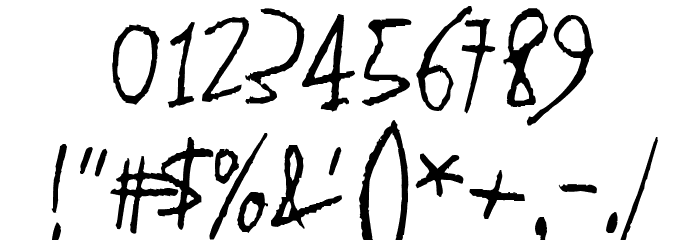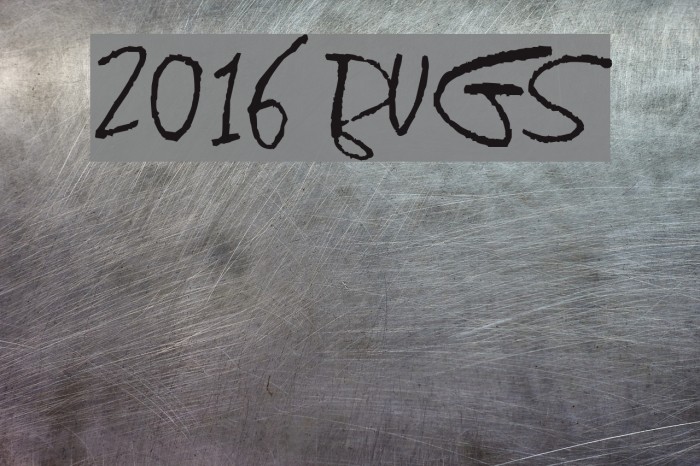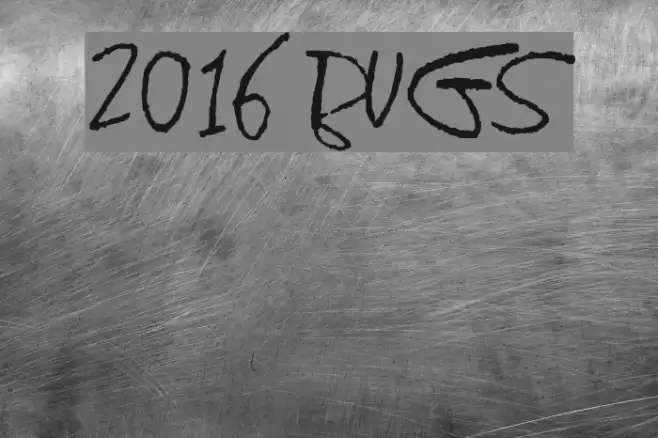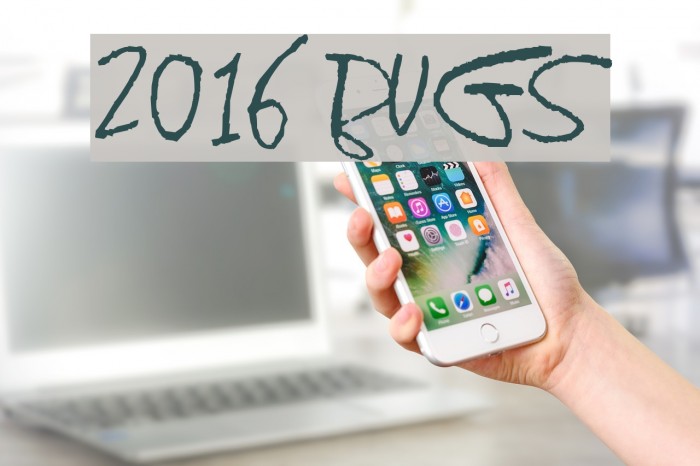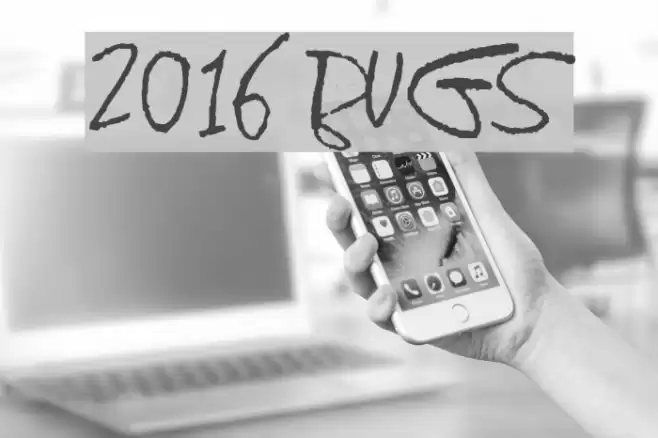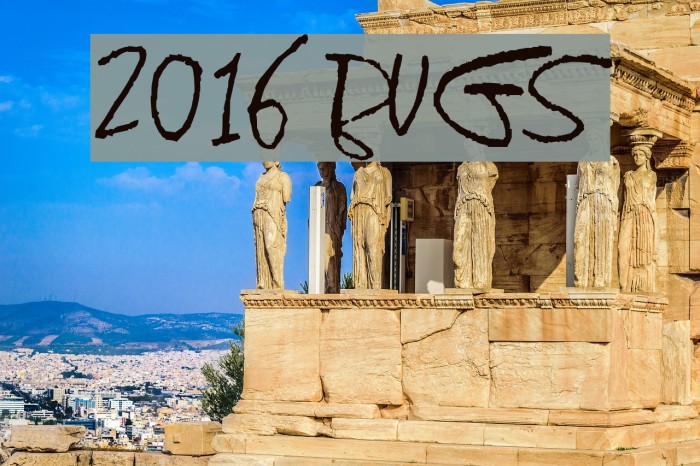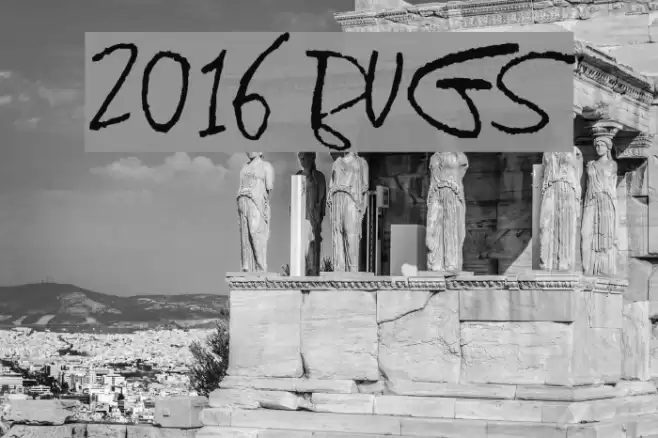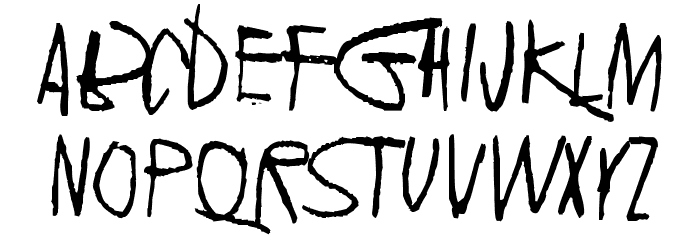
2016 Bugs Font
| Anwendungsfall | Logos, Headlines, Posters |
| Vorgeschlagene Projekte | Perfect for street art designs, edgy posters, album covers, or any project needing a rebellious touch. |